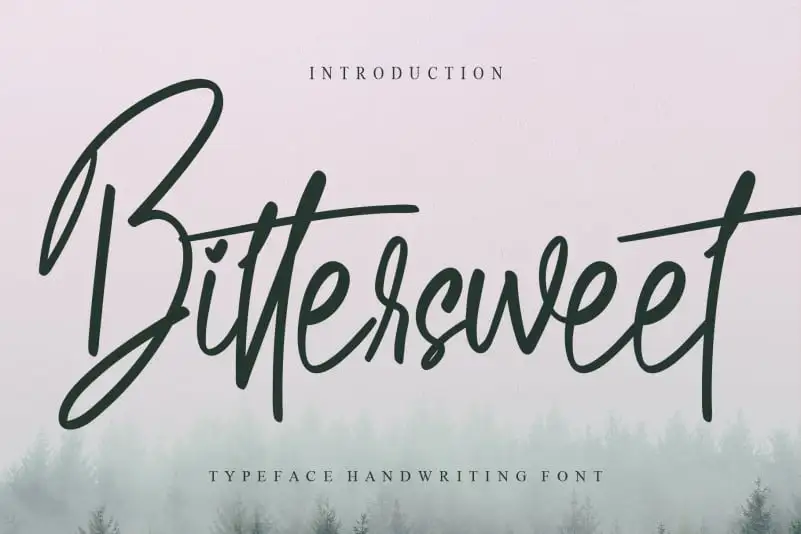
A fonte “Bittersweet Script Font” é uma criação do Designer CreativeLetter que oferece uma experiência única para os amantes de letras manuscritas. Suave e refinada, essa fonte tem um charme próprio, combinando elegância com criatividade. Ela traz consigo nuances sutis e detalhes cuidadosamente construídos, adicionando profundidade a qualquer projeto. A Bittersweet Script Font é perfeita para quem busca uma alternativa ao texto de tipo regular, oferecendo textura e individualidade que podem destacar seu design. Essa fonte é uma maravilha tanto para designers profissionais quanto para criativos leigos, pois permite explorar a linguagem visual em seus trabalhos. Seja você um designer web, gráfico ou editor de fotos, Bittersweet Script Font está aqui para tornar sua arte mais única e personalizada.